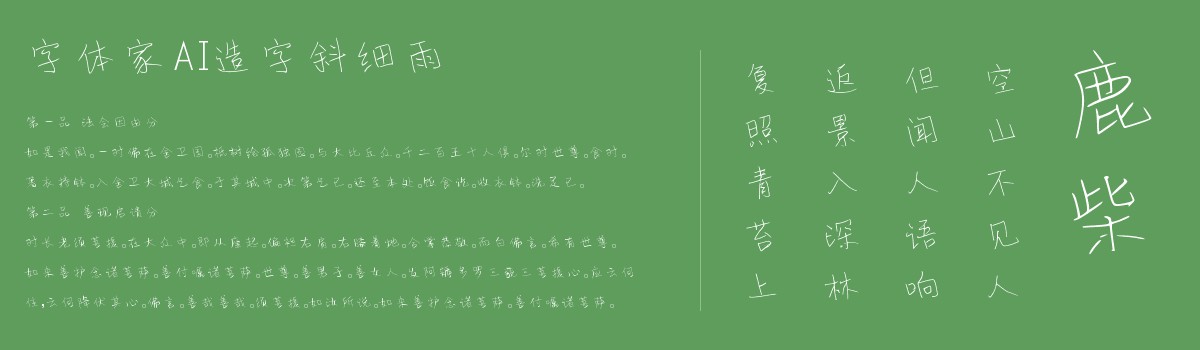
字体家AI造字斜细雨
字体家AI造字斜细雨是一款由字体家AI神笔造字生成的一款艺术字体,字体整体呈纤细的斜向姿态,笔画如细雨般轻盈舒展。线条流畅柔和,无生硬棱角,似手写笔触般自然连贯。字形偏瘦长,倾斜角度赋予灵动韵律,笔画粗细均匀,末端略带温润弧度,整体雅致轻柔,透着呼吸般的通透感。比较适合用于艺术类装饰文字,海报、网页、广告设计,室内装饰,平面标题设计、食品包装、品牌标志等。